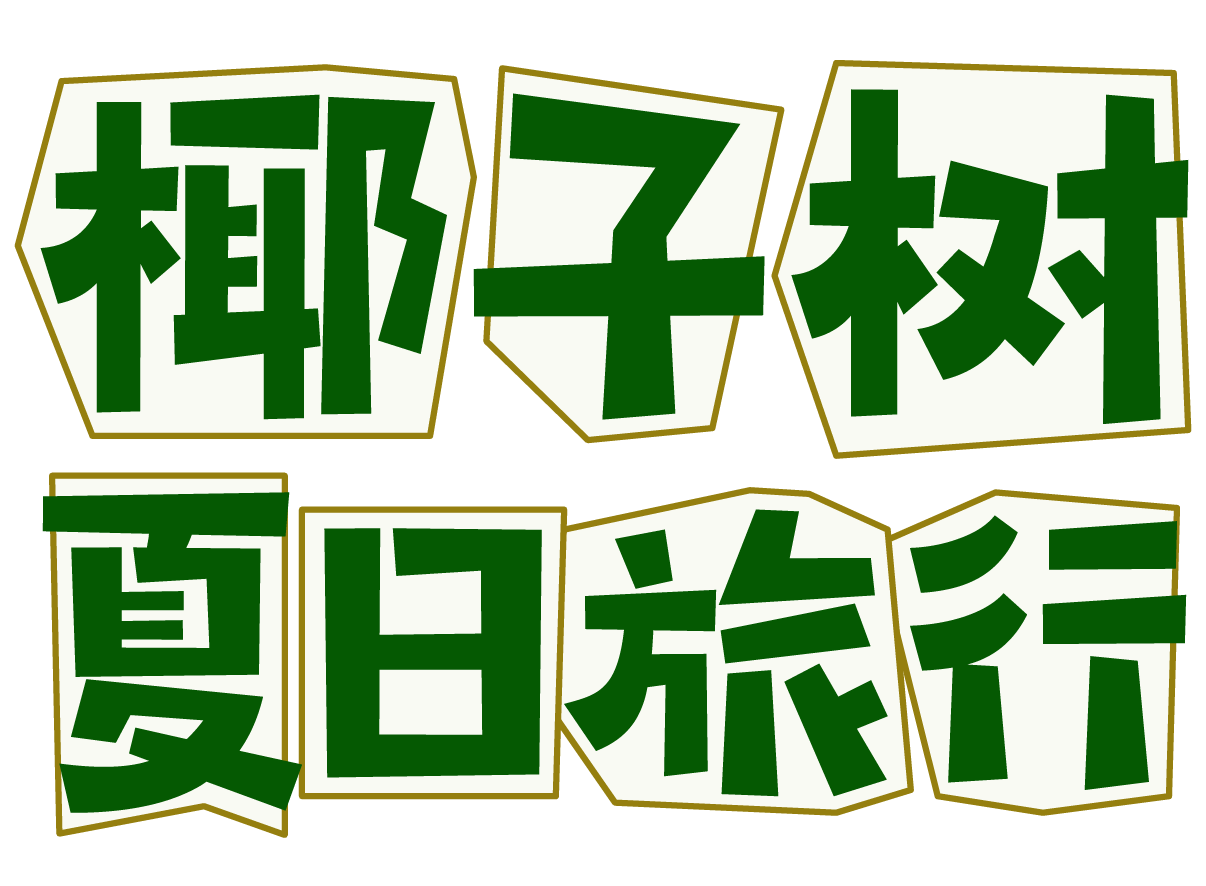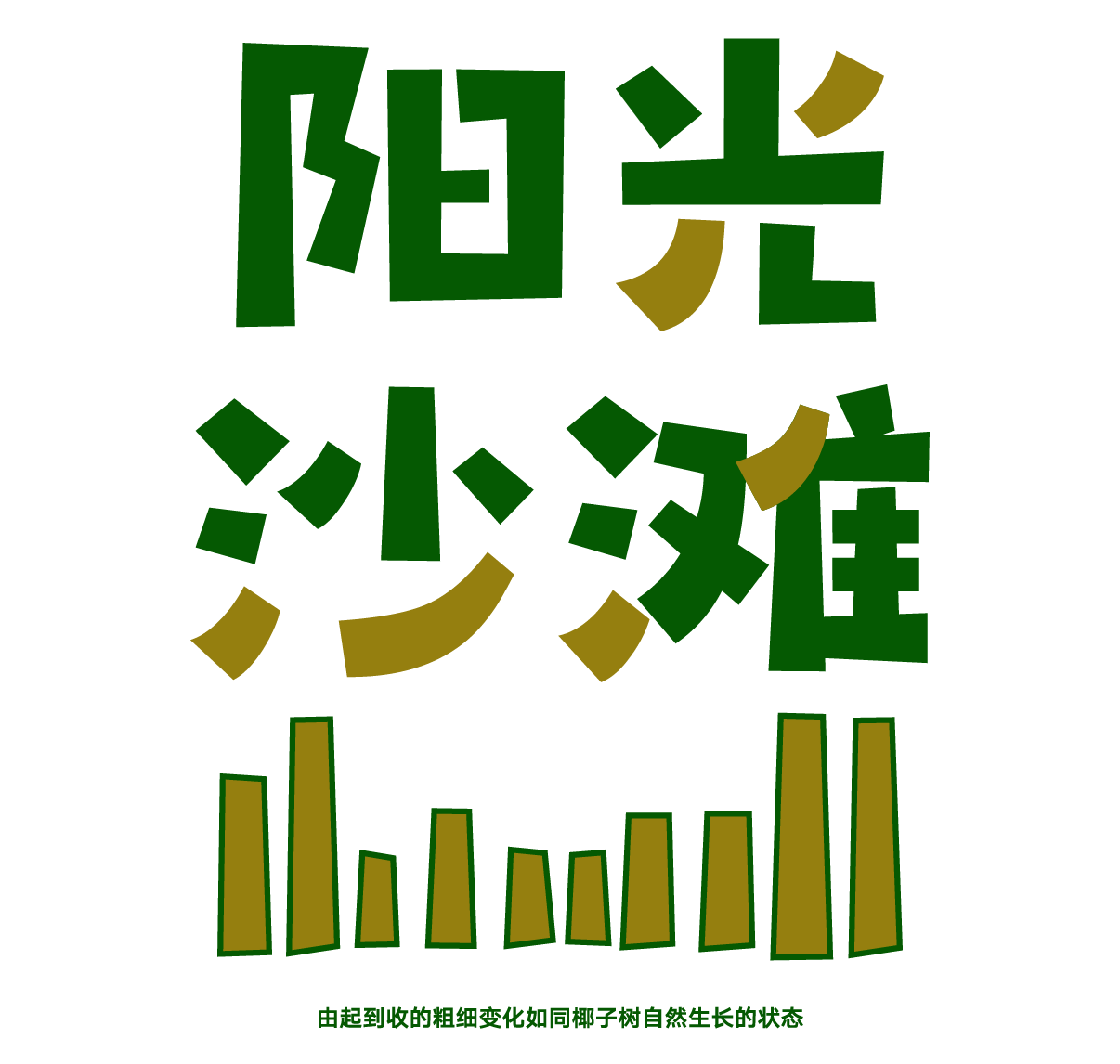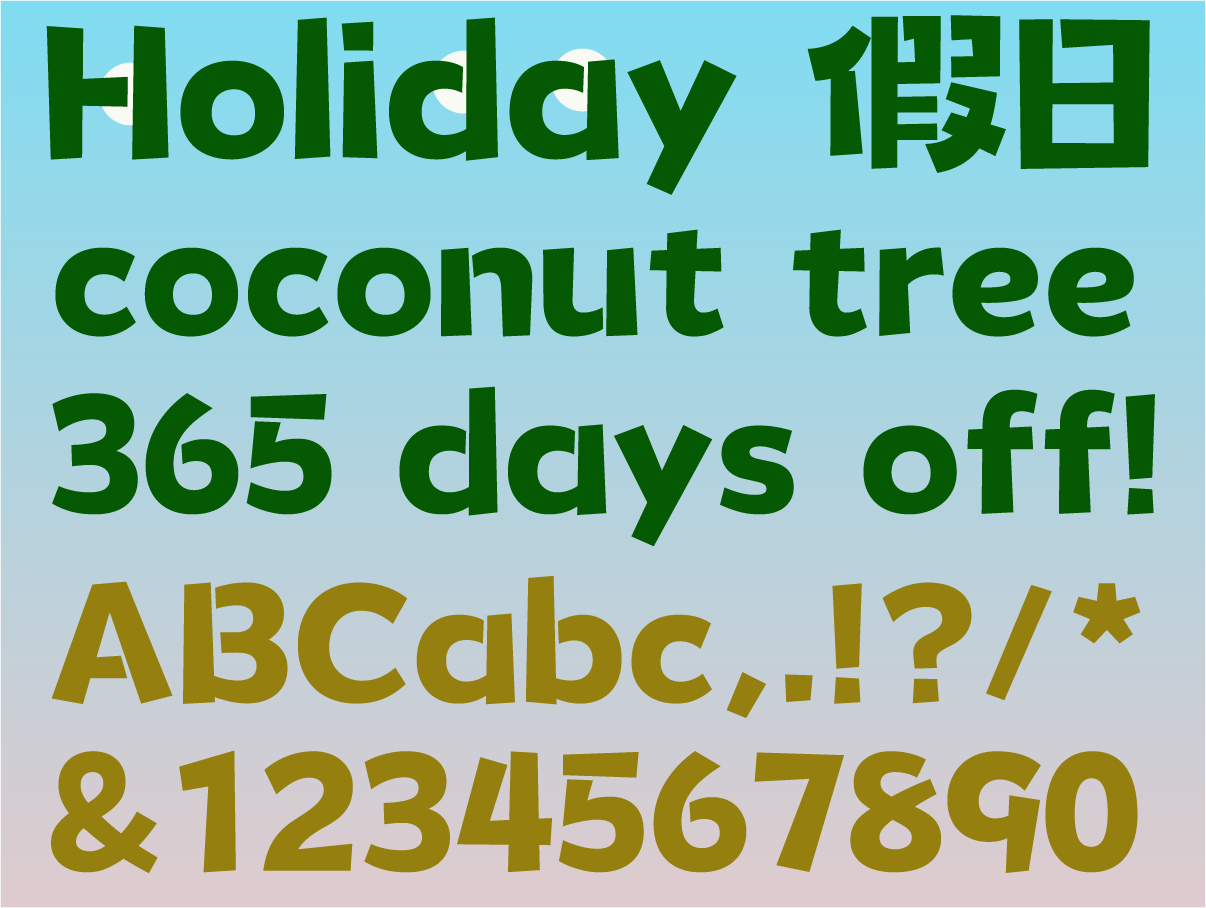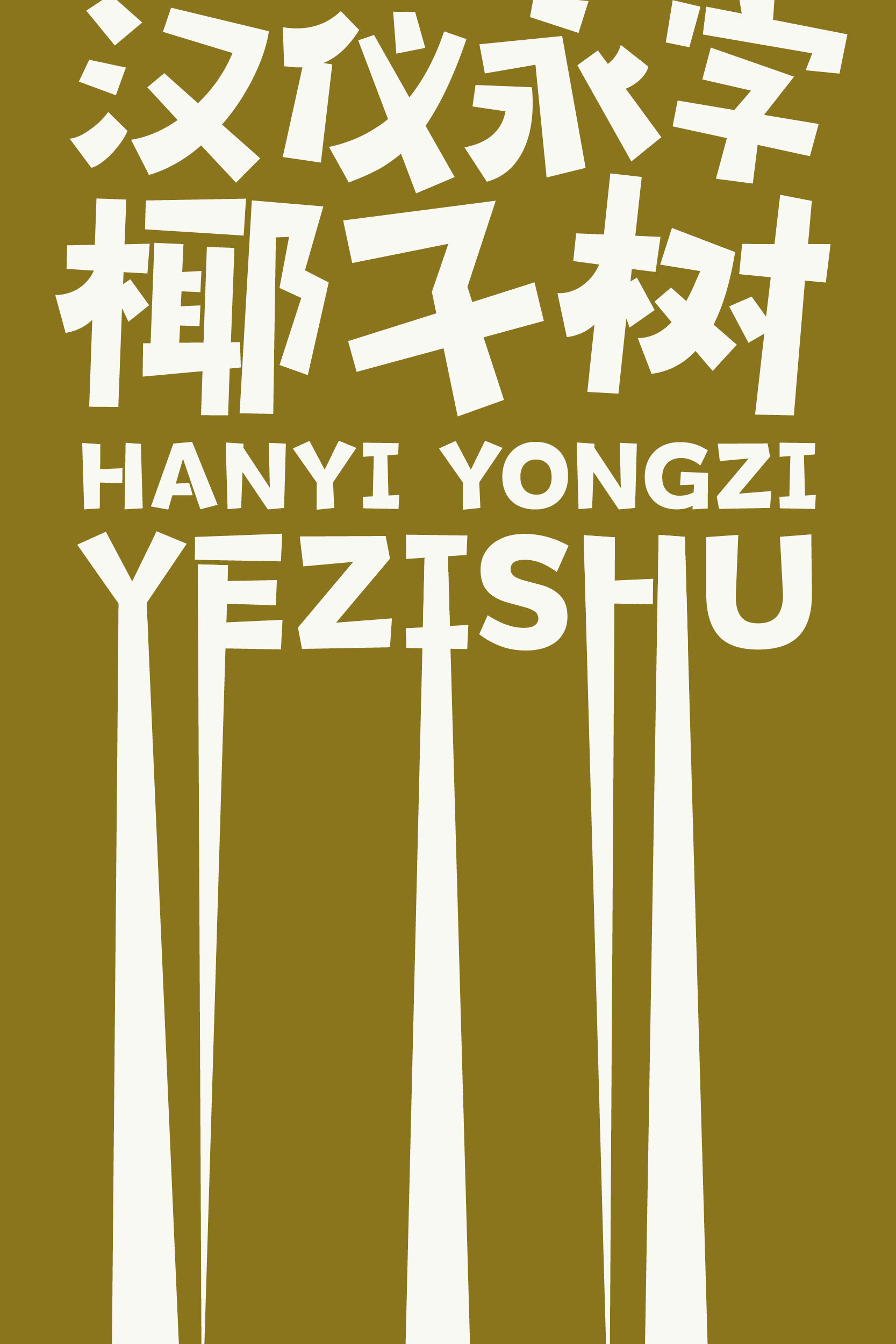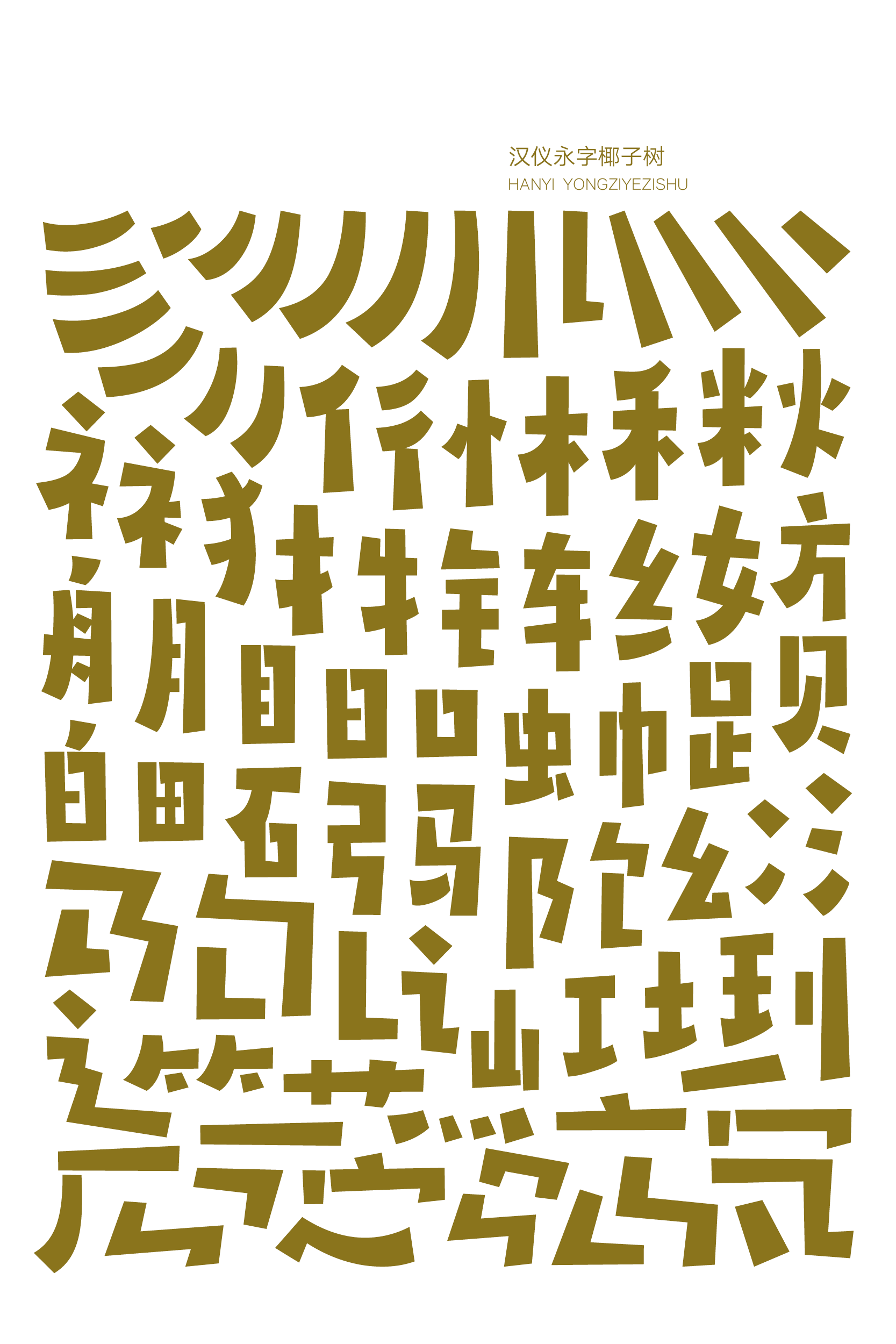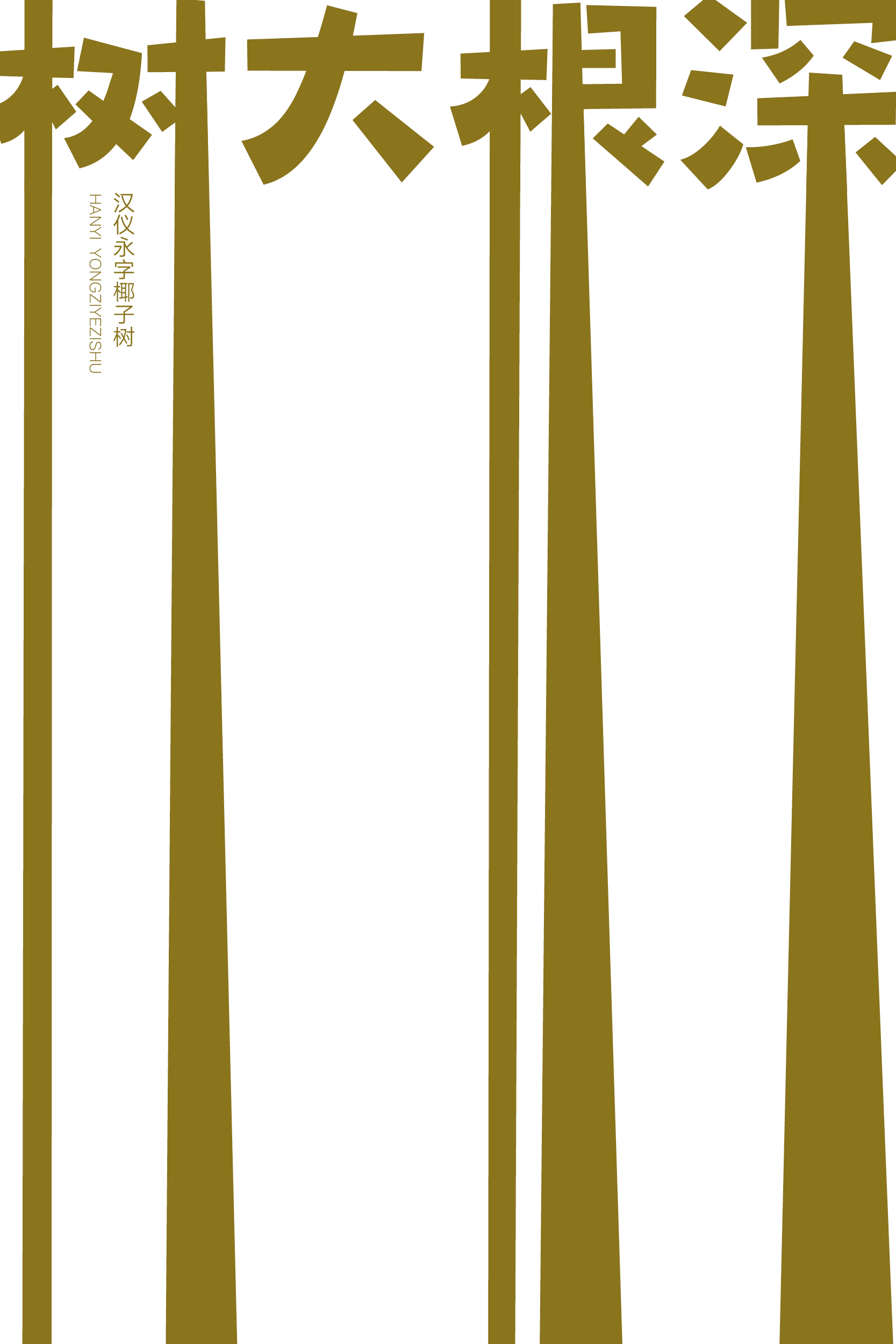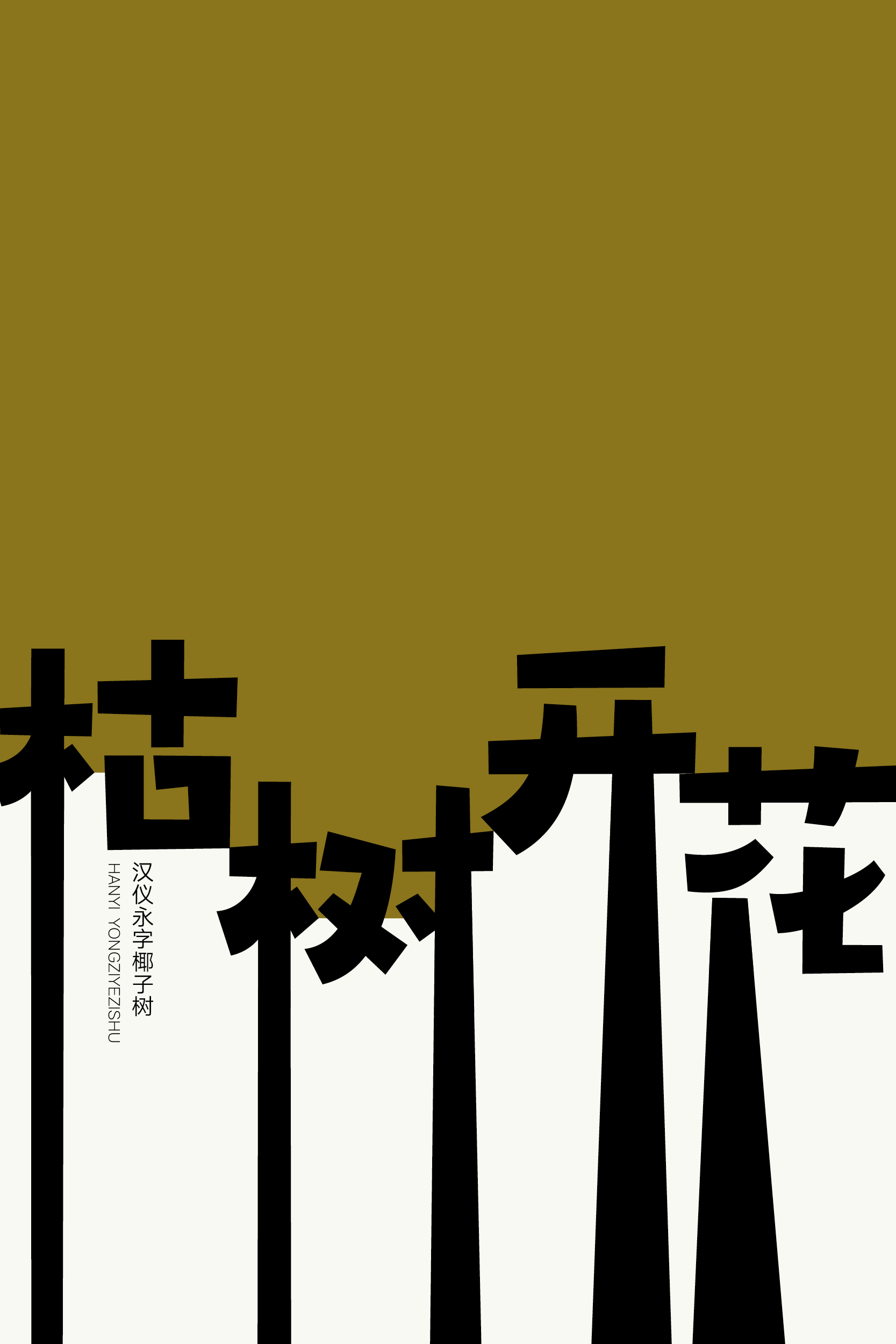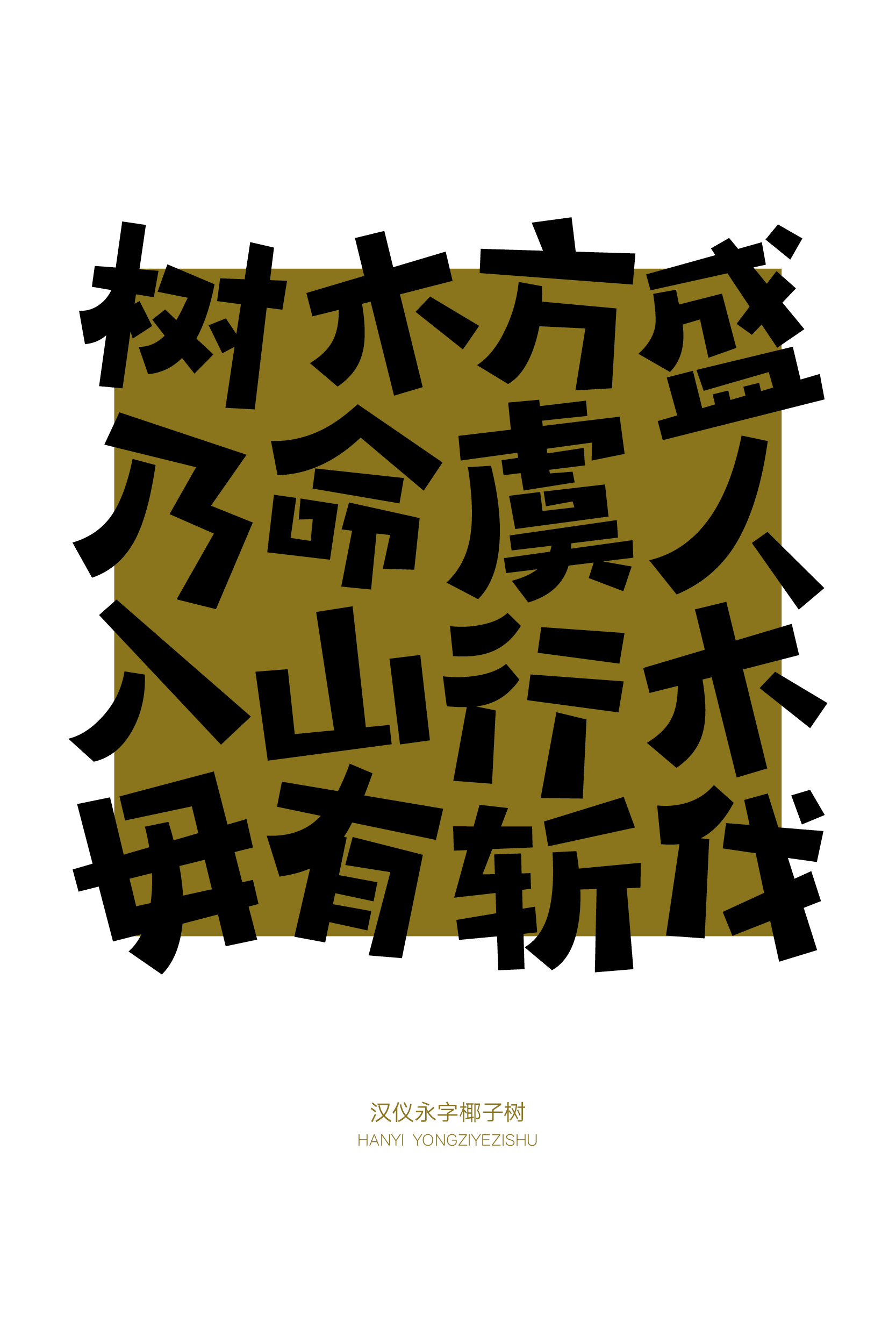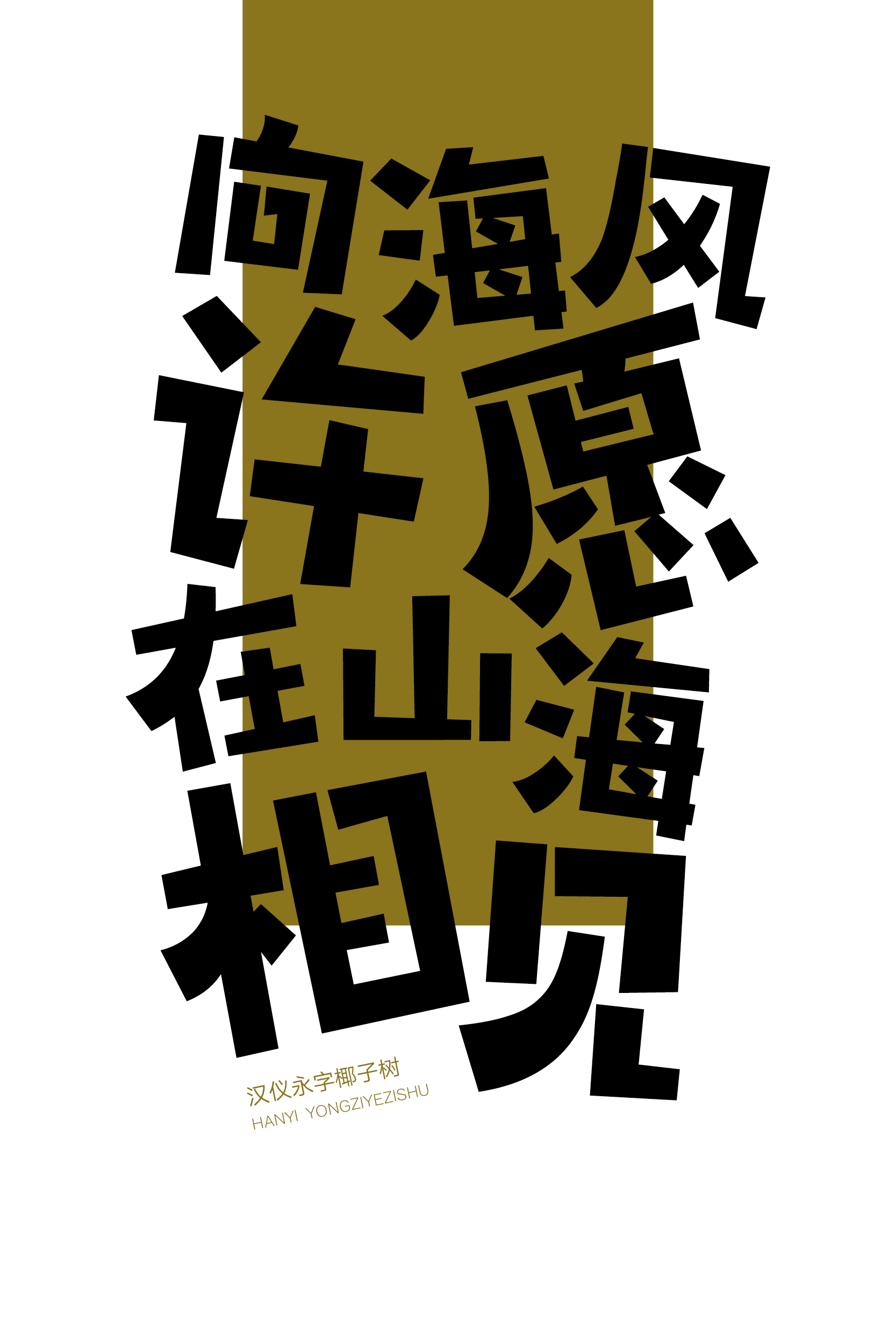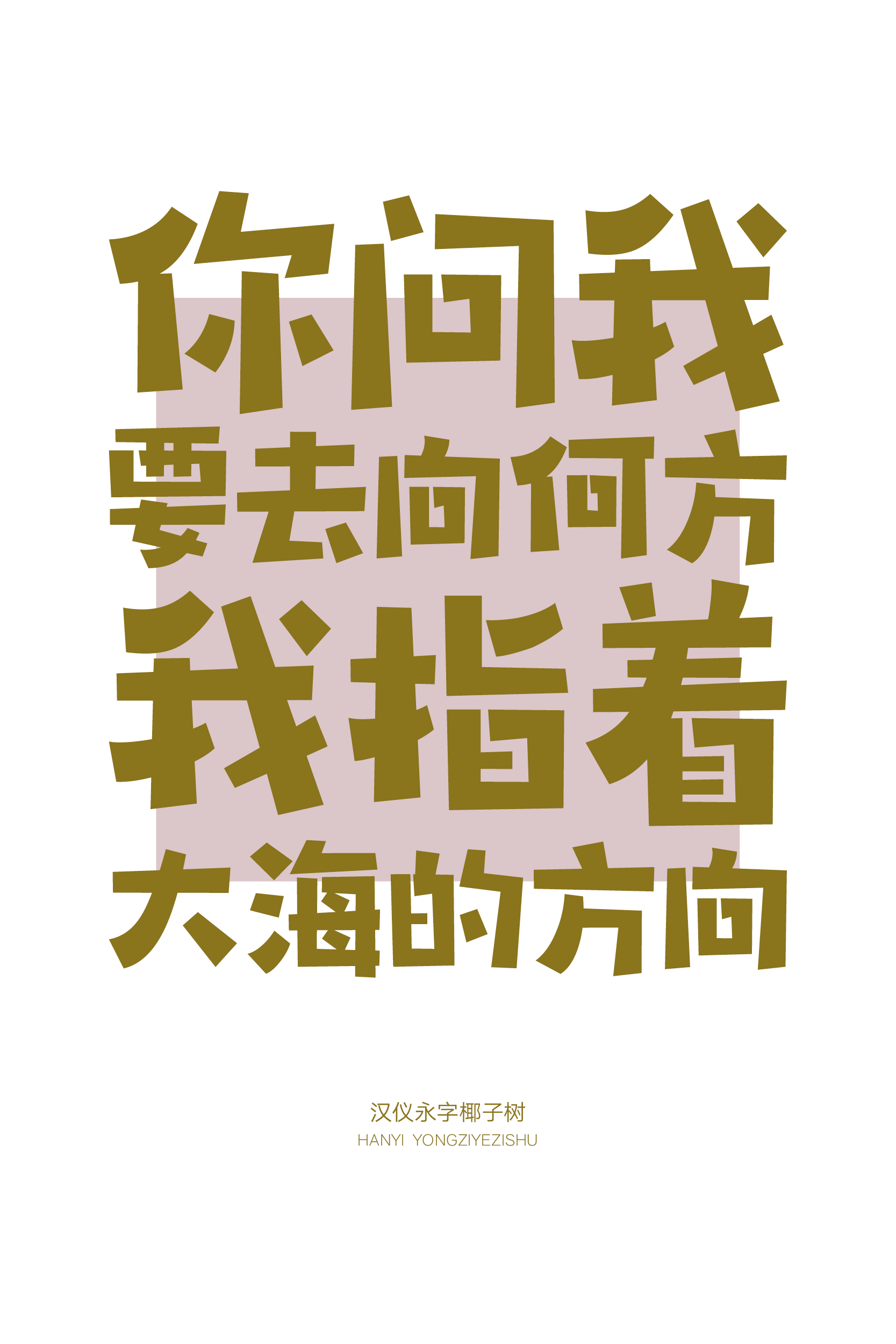
汉仪永字椰子树
阳光、沙滩、大海……就让汉仪永字椰子树这款由永字社创作的标题字体开启你的夏日度假模式:生动而活泼的造型如同椰子树,不论是应用于旅行宣传广告或是休闲餐饮包装,都传递着轻松和愉悦的心情,打出一行字,像是展开一道热带风景,消除了所有的烦恼和压力。
字形放松,错落活泼。
笔画简单稚拙。直线笔画构成椰子树笔直的树干,保留撇画弧线点缀其中。
部分笔形的减省连接造型简单而有趣味。
笔画的排布轻松随性,不完全搭接的处理加入透气感。
汉仪永字椰子树的西文部分同样有着活泼的字形和稚拙的笔画,并且保留笔画之间“喘口气”的处理。中西文搭配使用,从马尔代夫到北戴河都是乐园。